手描きイラスト&タイポ素材集
サインペインターとして活動する岩永茉帆氏、3sz chalkart(ミスズ チョークアート)という名前で活動する若井美鈴氏、チョークアーティスト・Asami、専門スクールのデジタルハリウッドでUIデザインやタイポグラフィの講師を務める米倉明男氏が監修を務めた黒、白、金のイラスト素材9,700点以上、オリジナルフォント30書体を収録した「手描きイラスト&タイポ素材集」がSBクリエイティブから2016年12月20日に発売された。
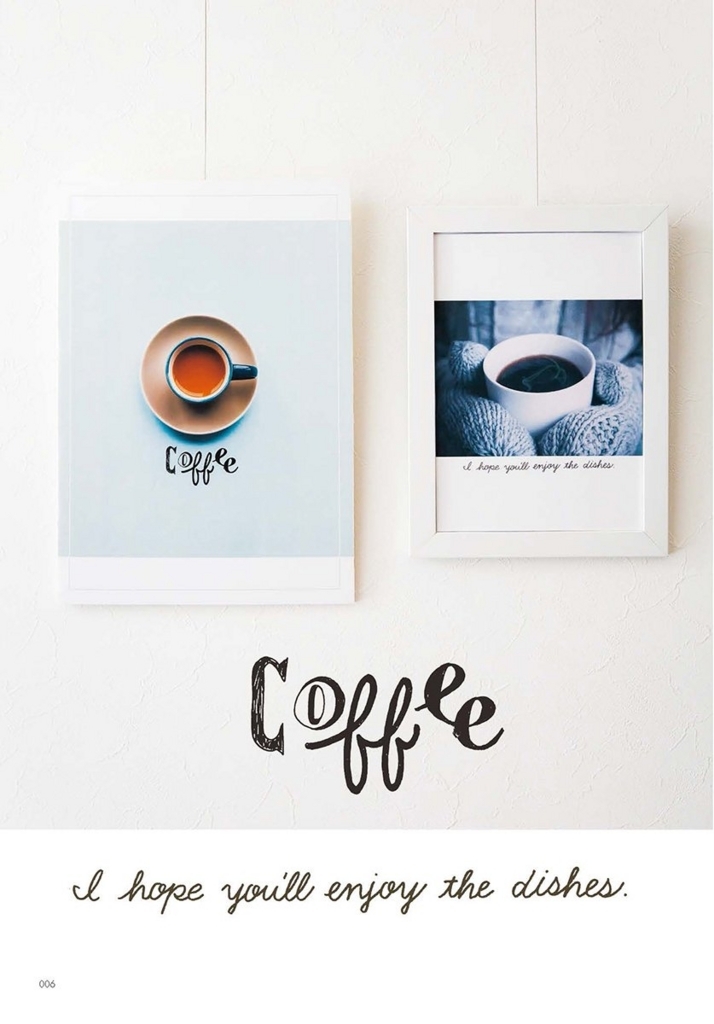
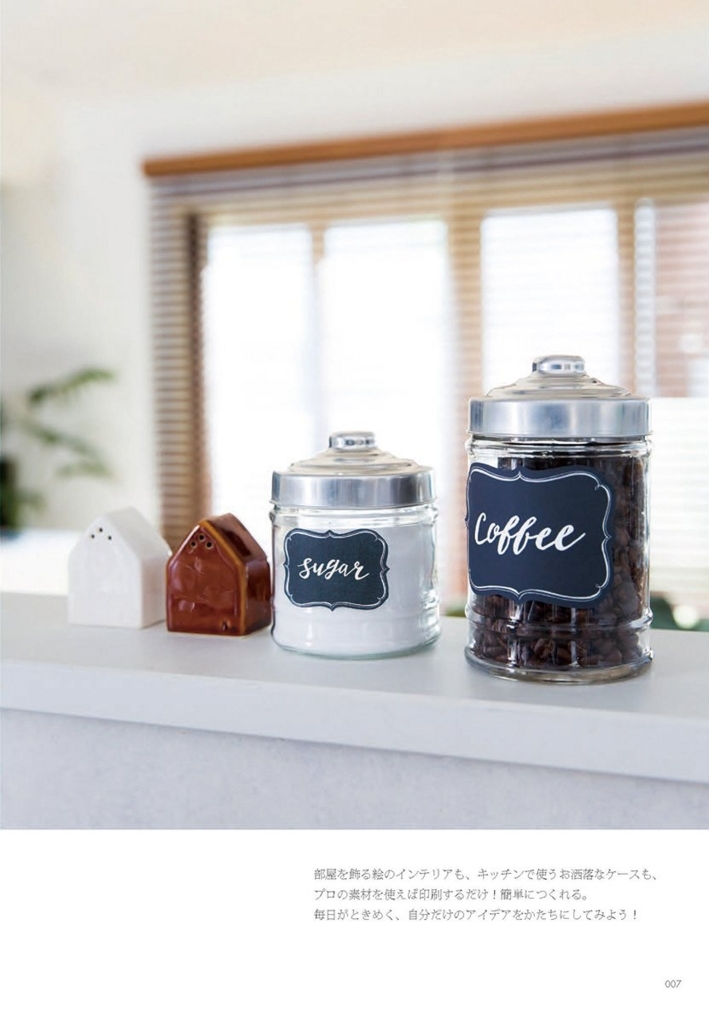
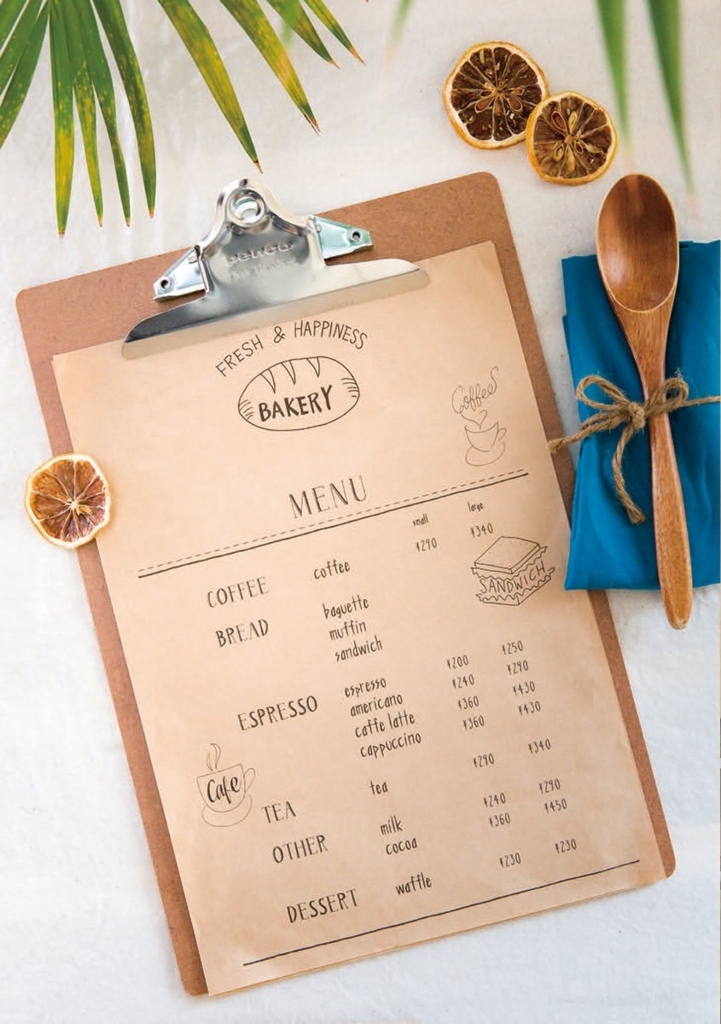
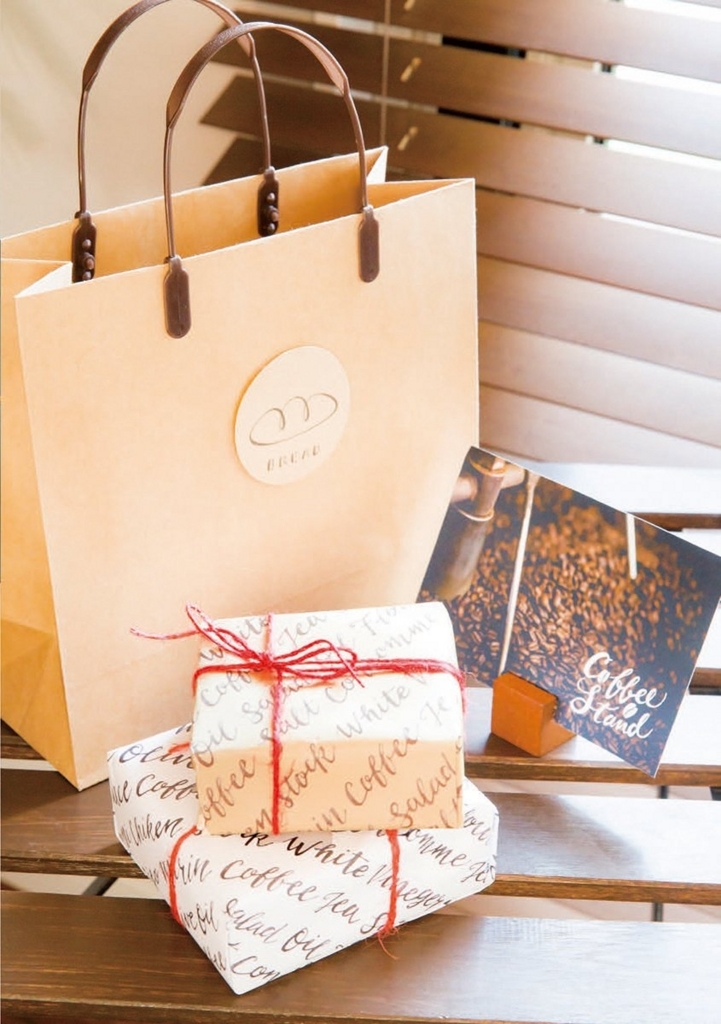
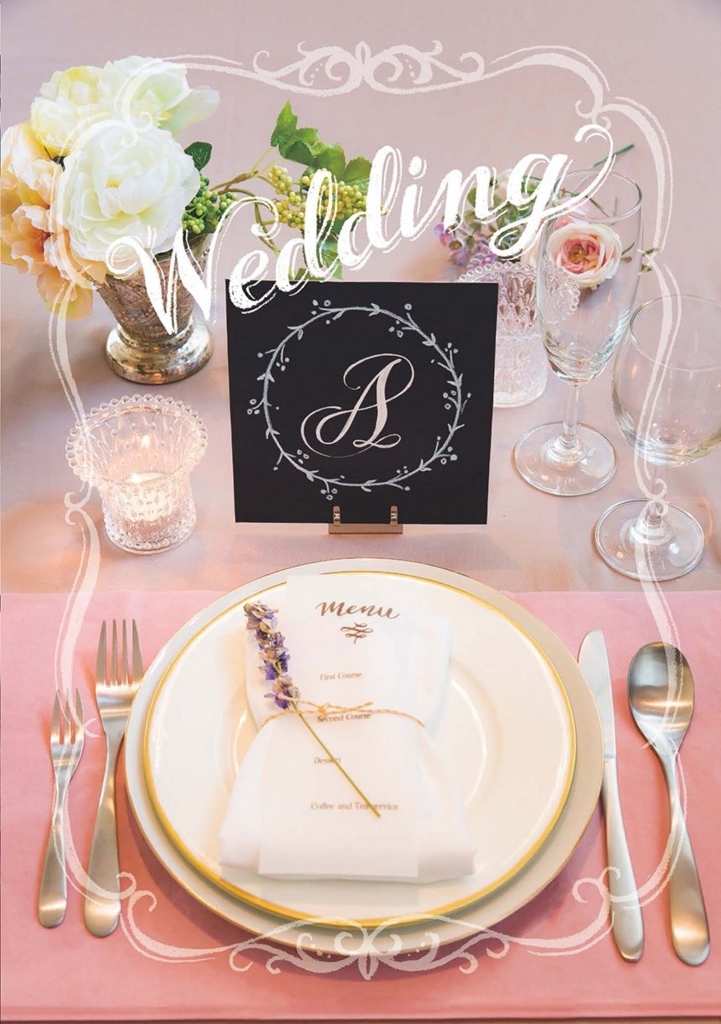
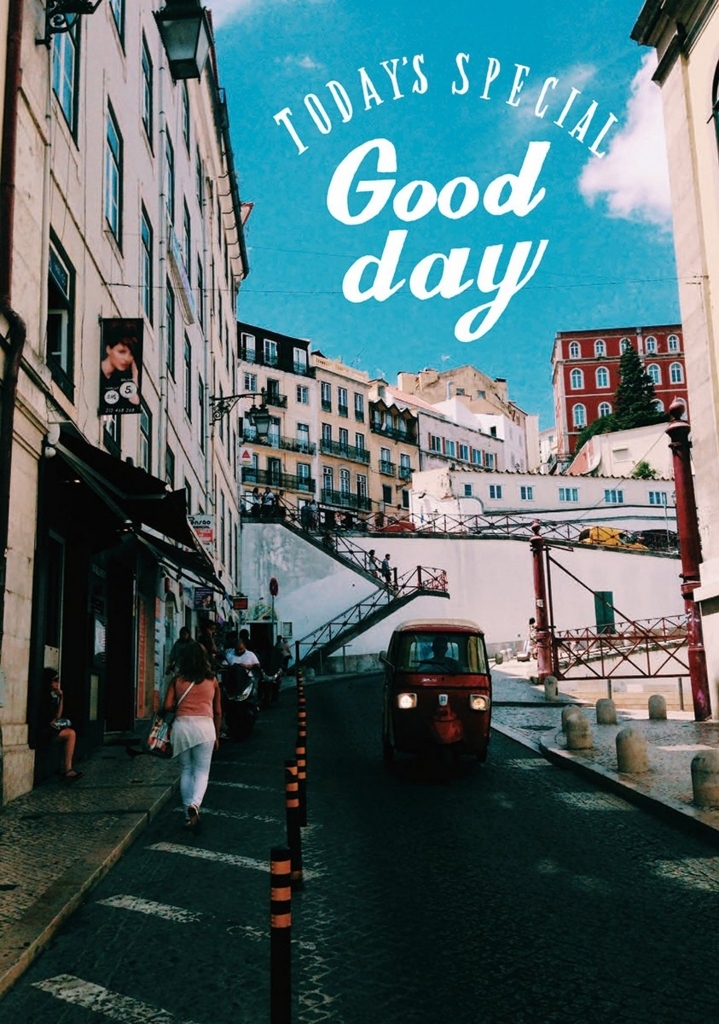
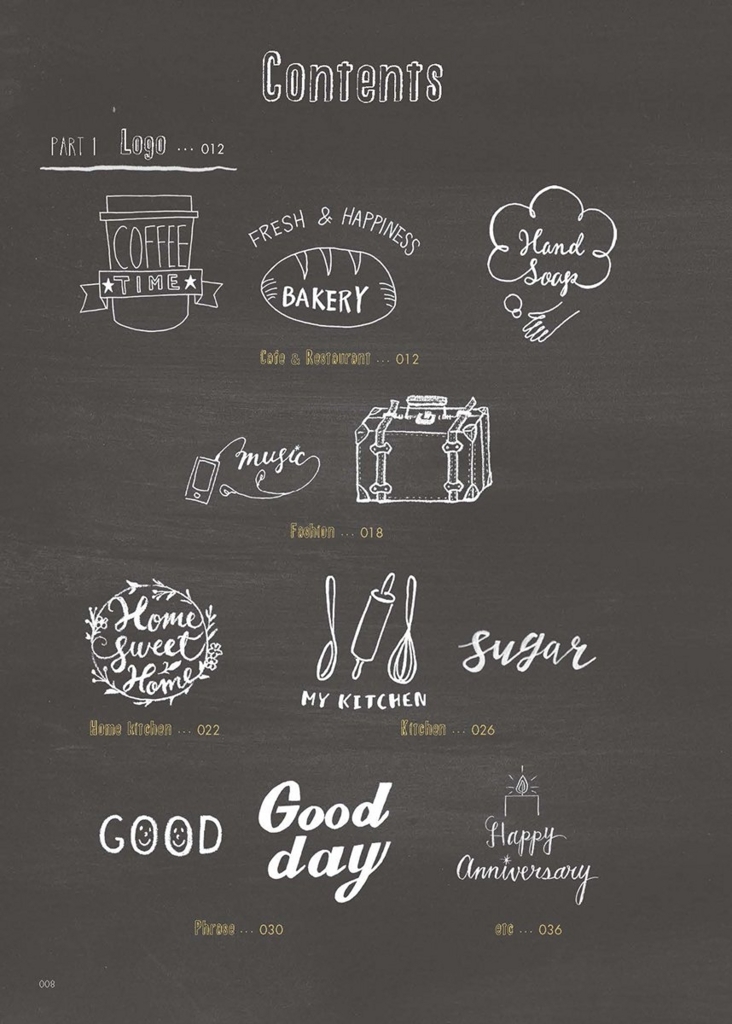
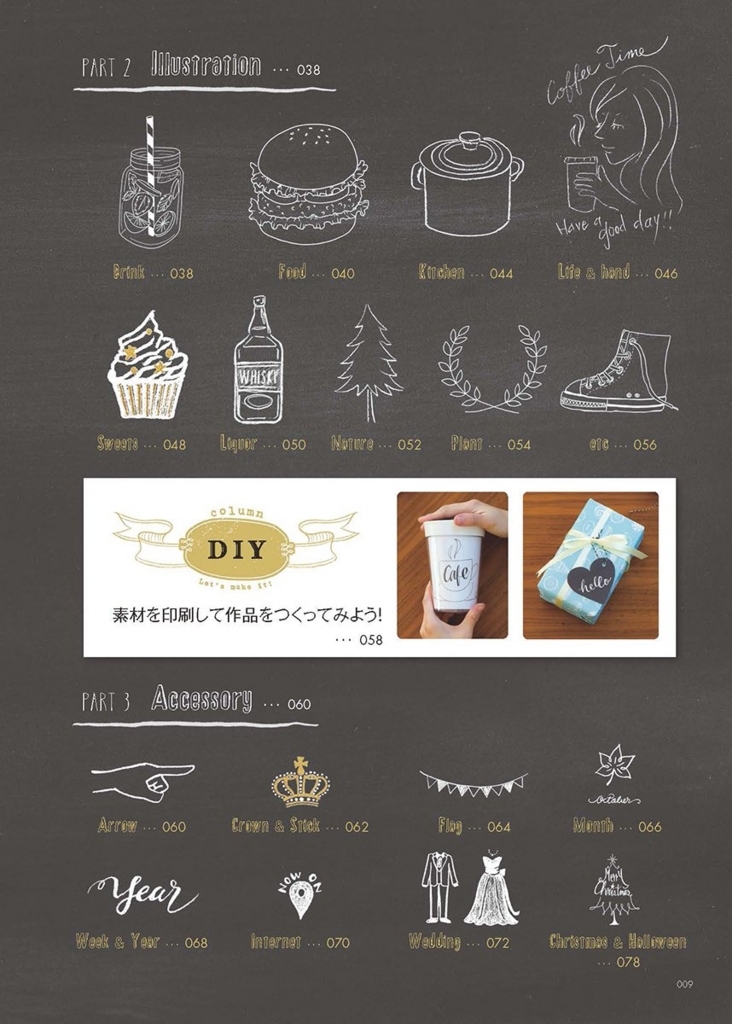
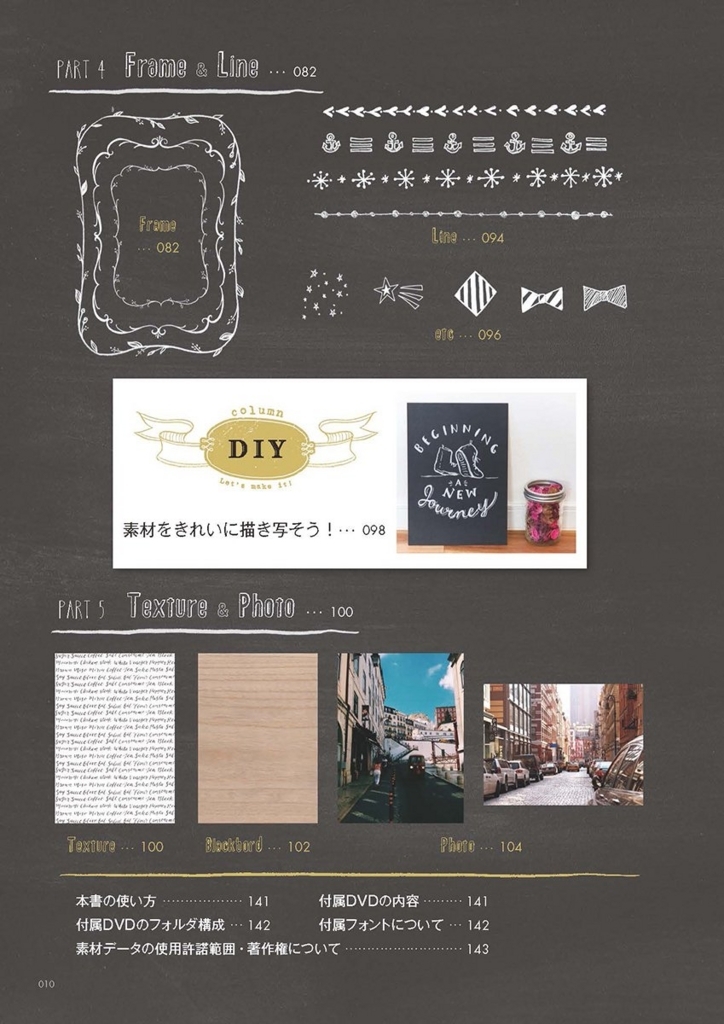
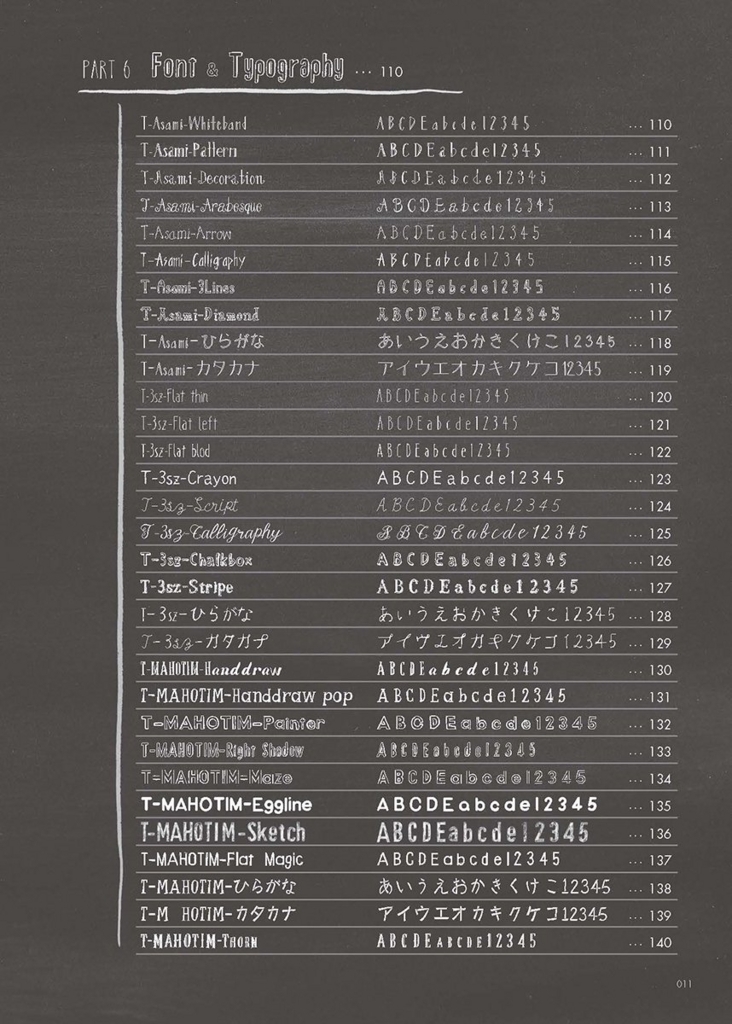
街で見かける流行りの手描き素材集
素材点数9700点以上、オリジナルフォント30書体収録!
カッコいいから可愛いまで
すぐには描けない「絶妙な手描き感」が揃っている
今、流行りの手描きイラストとタイポを集めた素材集です!
プロが描いた素材を使って
・カフェ、レストラン風のデザイン
・メニュー、ホームキッチン小物、インテリアポスター
・ハロウィンやクリスマスの飾り付け、ウェディングの手作り
・吹き出し、フレーム、矢印を使った面白アイデア
など
お洒落で目を惹く自分だけのアイデアをかたちにしてみてください。
■この本だけのポイント
・イラスト素材9700点以上、オリジナルの手描きフォントが30書体を収録。
・「黒」「白」に加えてデザインのワンポイントとして使える「金」の素材も付属。
・監修者が調整したベースラインまで揃っている手描きだけど読みやすいフォント。
・DIYの作成例をコラムとして収録。素材を複写する技など参考になります。
岩永 茉帆Profile●MAHOTIMの名前でサインペインターとして活動している。